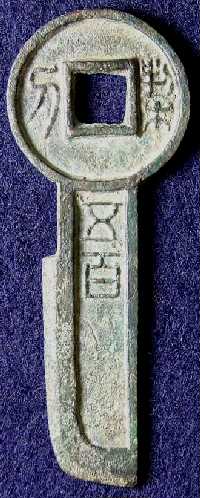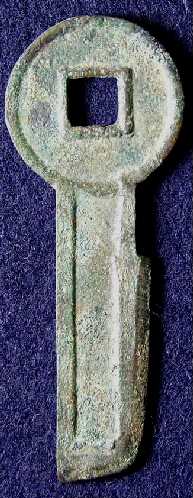
„‰¤ä͂̉ݕ¼EŒ_“
‰¤ä͂̉ݕ¼EŒ_“
Š¿Žš/Š¿Œê
“º/•s’èŒ`‘K
18.2g
‘S’·75.37mmA’¼Œa28.92mmAŒú‚³3.27mm
V‚̉¤ä͂̋ۓñ”NiŒã‚V”Nj‚̉ݕ¼B ã‰E‚ÉuŒ_i‰º•”‚Í–ØjvAã¶‚Éu“vA‰º‚ÉuŒÜ•SvB‘S‘Ì‚ÅuŒ_“ŒÜ•Sv‚Æ‚ ‚éB